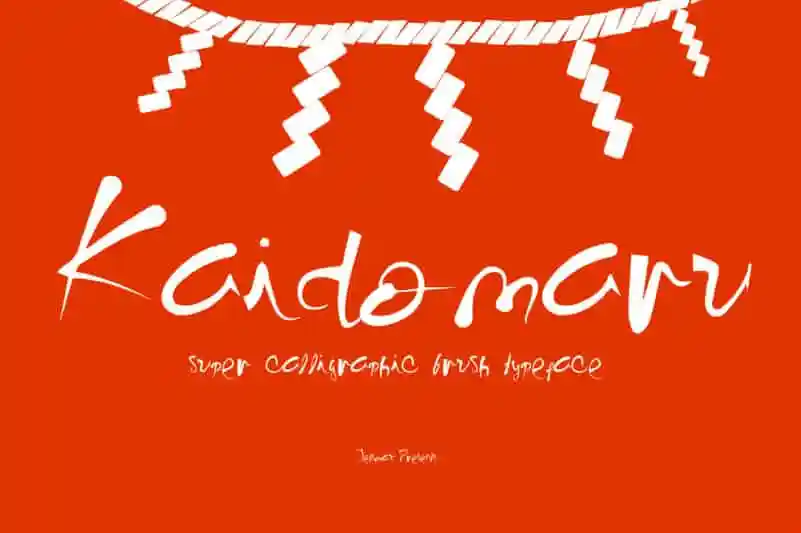
Kaidomaru Font – Download Grátis
A Kaidomaru Script Font é inspirada na autenticidade das festividades asiáticas, oferecendo uma sensação emocionante para seus projetos de design. Esta tipografia de esmalte transmite a vitalidade e o entusiasmo desses eventos culturais vibrantes, que são famosos por suas cores vivas e performances inovadoras. Como designer Jetsmax, aposta em um estilo deslumbrante e único para este tipo de letra, propiciando uma experiência única ao seu trabalho visual. Se você está pronto para explorar esses eventos culinários com Kaidomaru, então a fonte Kaidomaru Script é perfeita para ajudá-lo a alcançar esse objetivo.